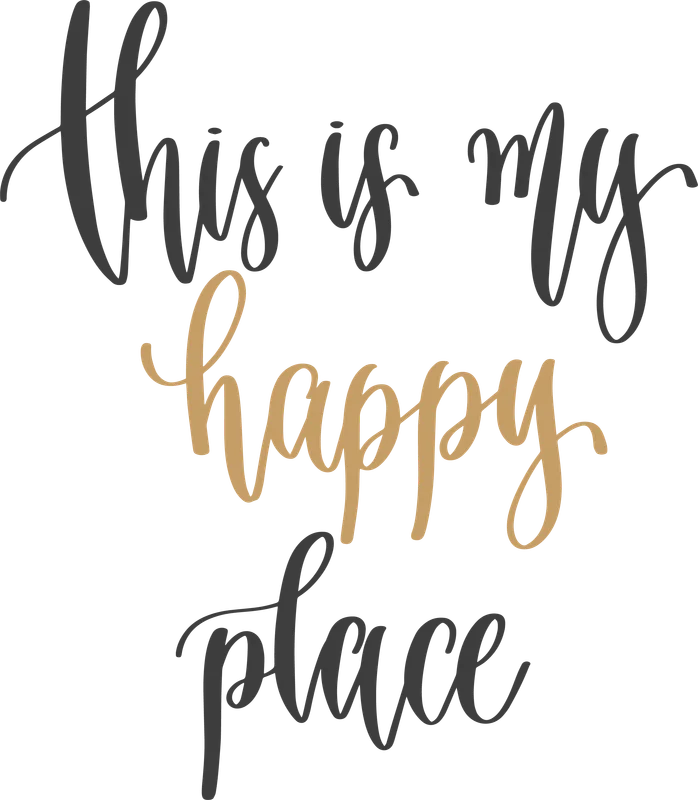
Câu nói "This is my happy place" font chữ thư pháp
Câu nói "This is my happy place" font chữ thư pháp — In hình câu nói "This is my happy place" với font chữ thư pháp độc đáo, mang đến cảm giác ấm áp và bình yên. Phù hợp in chuyển nhiệt lên áo, túi, cốc.
Trong hình có: chữ viết, câu nói
Phong cách: line-art · Cảm giác: bình yên
Tông màu chủ đạo: xám, cam